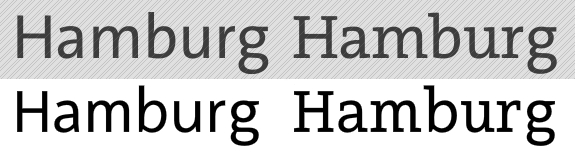
German Type: Arventa & Arventa Slab
GTF stellt Ingo Preuß’ neuestes Schriftprojekt vor, das Arventa-Schriftsystem.
Das Arventa Schriftsystem teilt sich auf in zwei auf einander abgestimmte Schriftfamilien: eine Sans- und eine Slab-Familie. Die Ausgangsform des Systems bildet die Arventa Sans. Die Arventa Slab ist jedoch keine Sans mit angeklebten Serifen; sie wurde ebenso feinfühlig von grundauf entwickelt wie die Sans. Die Arventa vereint geometrische und humanistische Gestaltungselemente um optimale Lesbarkeit zu erreichen. Wenn hochwertige typographische Aufgaben gute Lesbarkeit erfordern, bieten beide Arventa Familien eine perfekte Auswahl.
Jede Arventa Familie enthält sieben Fetteabstufungen (Thin, Light, Regular, Medium, Bold, Black und UltraBlack) jeweils zuzüglich der Kursiven. Jeder einzelne Font enthält über 1000 Buchstaben und ist gewissenhaft nach dem bewährten GTF-UNI-Standard entwickelt. Alle Fonts enthalten einen umfangreich latinischen Zeichensatz nebst Kapitälchen sowie Kyrillisch und Griechisch. Ebenso sind umfangreiche Zahlenformate (tabular und proportional), Hoch- und Tiefstellungen und Brüche enthalten, die einfach über OpenType Features anzuwenden sind.
So vielseitig die heutigen typografischen Aufgaben auch sind, das Arventa Schriftsystem bietet Ihnen alles für gute Typografie.
Sehr schön! … und einer bekannten Schrift nicht gerade unähnlich:
Einige Feinheiten finde ich auf den ersten Blick besser als in der Thesis, zum Beispiel das g und ß (das im TypeTester leider nicht eingegeben werden kann).
Ich würde sie mir gerne mal gedruckt anschauen – das geht aber leider nicht, da man sich kein Muster herunterladen kann! :?
PS: Enthält die Arventa Schriftfamilie auch einen Binde Strich? :twisted:
Auf den ersten Blick sehr schön :biglove: – aber schon recht nahe bei der Thesis
h, n und m bei der Slab-Variante scheinen für meinen Geschmack zu schmal zu sein, vor allem im Vergleich zum gemeinen u
e ist mir zu Rotis ähnlich und mit den beiden S s in der Slab kann ich mich auch nicht wirklich anfreunden.
geht das nur mir so?
ß (das im TypeTester leider nicht eingegeben werden kann).
doch, kann es – und ich ?nde es, ehrlich gesagt, ziemlich …
ich dachte erst, da wäre versehentlich das versal-ß dazwischengerutscht.
auf den zweiten blick: die unterschiede zwischen arventa sans und thesans sind übersichtlich. in fast allen fällen erscheint mir die buchstabenform bei der thesans organischer. die arventa slab und die theserif trennt in der aufrechten auch nicht wesentlich mehr. jeweils auffälligster unterschied: ›b‹, ›d‹, ›p‹ etc. haben bei der arventa einen kleinen sporn.
am interessantesten ist aber, die kursiven der beiden egyptiennes zu vergleichen. die arventa slab, die in der aufrechten – wie theserif – dynamisch wirkt, hat hier einen statischen touch, der mit der formensprache der schrift an sich kollidiert. sie nimmt das genre ›slab-serif‹ zu ernst. in theserif wird damit spielerischer, souveräner umgegangen.
gerade das ›i‹ und das ›w‹ ?nde ich bei der theserif um klassen besser. es muss doch nicht an jeder ecke eine (beidseitige) serife kleben, um klarzumachen: ich bin keine sans!